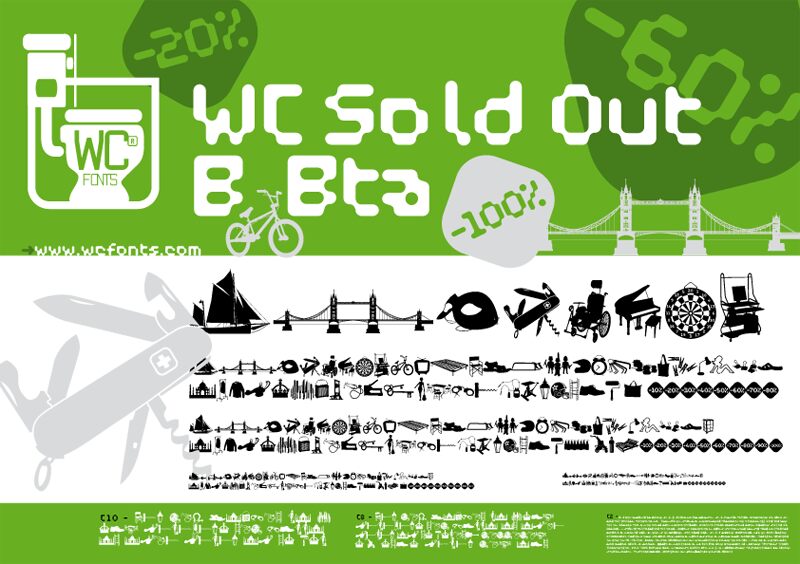
WC Sold Out B to darmowy font typu dingbat od WC Fonts, który przypomina wycinki z albumu pełnego codziennych osobliwości i grafik z epoki pin-up. Zestaw łączy krągłe kobiece figury z solidnymi przedmiotami – rybą, naczyniami, szpulkami nici, korkociągiem czy gitarą – narysowanymi wyrazistymi, czarnymi kształtami, które bardziej przypominają wycinanki niż klasyczne ornamenty.
Dzięki temu łatwo użyć go jako darmowego kroju w akcentach na plakatach, okładkach zinów, menu barowych, opakowaniach w stylu retro, metkach czy zabawnych tytułach, gdzie jedno mocne ikoniczne oznaczenie załatwia sprawę. Świetnie sprawdza się w kolażach i krótkich formach graficznych, ponieważ motywy są różnorodne, ale utrzymane w tym samym płaskim, ręcznie wycinanym stylu.